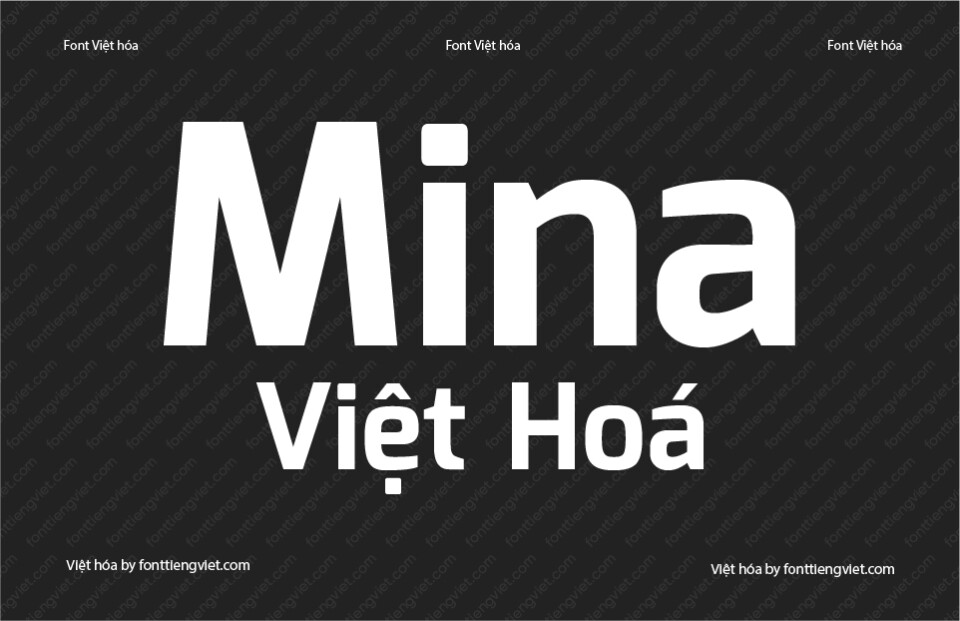
Font Việt hóa 1FTV VIP Mina Bold
Font Việt hóa 1FTV VIP Mina Bold: Sự lựa chọn hoàn hảo cho thiết kế học đường
Giới thiệu về Font Việt hóa 1FTV VIP Mina Bold
Trong thế giới thiết kế đồ họa hiện nay, việc lựa chọn một bộ font chữ phù hợp đóng vai trò quan trọng trong việc truyền tải thông điệp và cảm xúc. Font Việt hóa 1FTV VIP Mina Bold nổi lên như một hiện tượng nhờ sự kết hợp tinh tế giữa nét hiện đại và tính ứng dụng cao. Đây là phiên bản đặc biệt được tinh chỉnh kỹ lưỡng để phù hợp với bảng mã tiếng Việt, giúp người dùng không còn lo lắng về lỗi hiển thị dấu hay các ký tự đặc biệt. Đối với các bạn học sinh và giáo viên, việc sử dụng Font Miễn Phí chất lượng như Mina Bold sẽ giúp các bài thuyết trình hay tài liệu học tập trở nên sinh động và chuyên nghiệp hơn hẳn.
Đặc điểm nổi bật của bộ font chữ này
Thiết kế đậm chất hiện đại và trẻ trung
Font Việt hóa 1FTV VIP Mina Bold sở hữu những đường nét dày dặn, chắc chắn nhưng không kém phần mềm mại. Kiểu dáng Bold (đậm) giúp font chữ này cực kỳ nổi bật khi được sử dụng làm tiêu đề cho các ấn phẩm truyền thông hoặc poster sự kiện trường học. Sự cân đối trong cấu trúc các con chữ tạo nên một cảm giác dễ nhìn, thân thiện với người xem ở mọi lứa tuổi. Đặc biệt, bộ font này đã được tối ưu hóa để hiển thị sắc nét trên cả màn hình máy tính lẫn khi in ấn ra giấy.
Khả năng tương thích và ứng dụng đa dạng
Một trong những lý do khiến Font Việt hóa 1FTV VIP Mina Bold được yêu thích chính là khả năng ứng dụng linh hoạt. Bạn có thể sử dụng nó để thiết kế bìa sách, làm slide bài giảng PowerPoint, hoặc tạo ra những tấm thiệp chúc mừng thầy cô giáo. Với bảng ký tự đầy đủ các dấu câu tiếng Việt, người dùng có thể tự tin sáng tạo mà không gặp bất kỳ rào cản kỹ thuật nào. Việc cài đặt font cũng vô cùng đơn giản, chỉ với vài thao tác cơ bản là bạn đã có thể sở hữu bộ gõ nghệ thuật này trên máy tính cá nhân.
Lợi ích khi sử dụng Font Việt hóa 1FTV VIP Mina Bold trong giáo dục
Môi trường học đường luôn cần sự sáng tạo nhưng vẫn phải đảm bảo tính chuẩn mực. Font Việt hóa 1FTV VIP Mina Bold đáp ứng tốt cả hai tiêu chí đó. Khi sử dụng font chữ này, các bài báo tường hay tập san của lớp sẽ có một diện mạo hoàn toàn mới, thu hút sự chú ý của người đọc ngay từ cái nhìn đầu tiên. Ngoài ra, việc tiếp cận với các bộ font được Việt hóa chuẩn giúp các bạn học sinh hình thành tư duy thẩm mỹ tốt hơn và biết cách trình bày văn bản một cách khoa học, đẹp mắt.
Tóm lại, Font Việt hóa 1FTV VIP Mina Bold là một công cụ đắc lực dành cho những ai đam mê sáng tạo và muốn nâng tầm sản phẩm thiết kế của mình. Sự chỉn chu trong từng nét chữ và độ tương thích hoàn hảo với tiếng Việt chính là điểm cộng lớn nhất. Nếu bạn đang tìm kiếm một giải pháp tối ưu cho các dự án sắp tới, đừng ngần ngại tìm hiểu thêm tại Font Miễn Phí, Font Việt Hóa, Font Việt hóa 1FTV VIP Mina Bold để tải về và trải nghiệm ngay hôm nay. Hy vọng rằng bộ font này sẽ mang lại nguồn cảm hứng mới mẻ cho công việc học tập và giảng dạy của bạn.